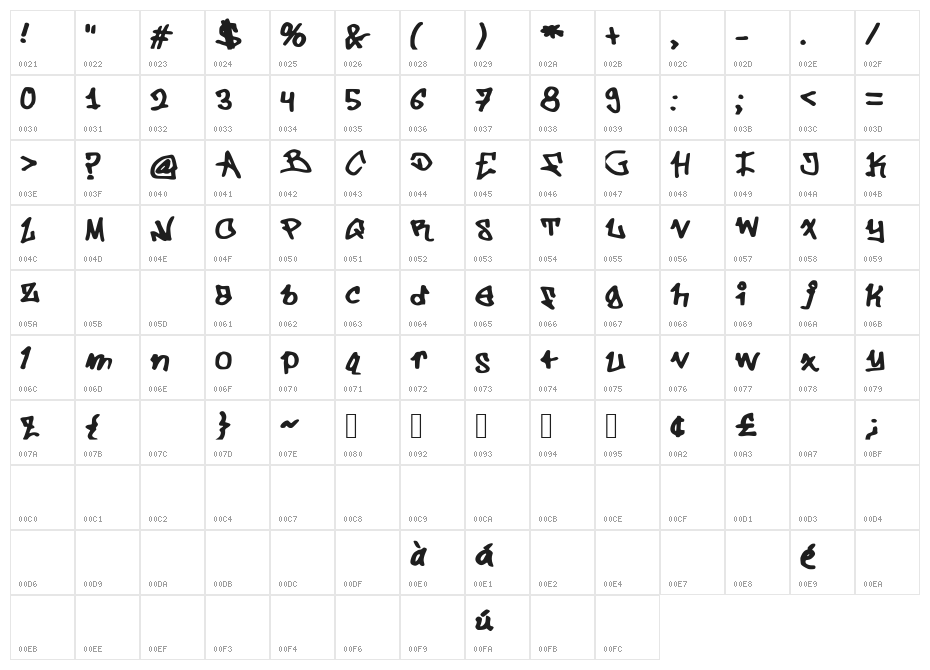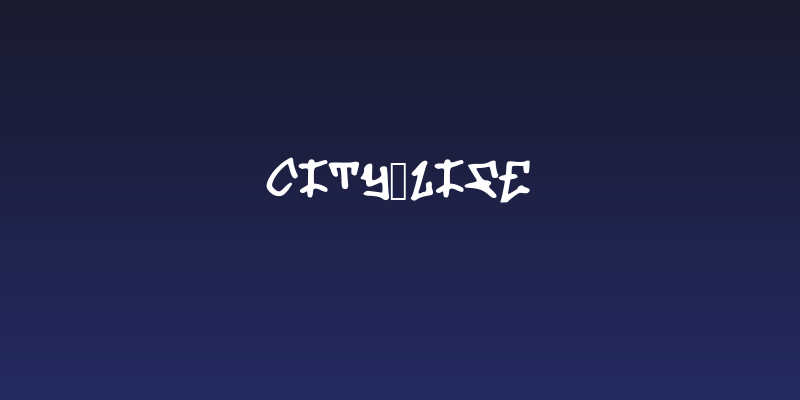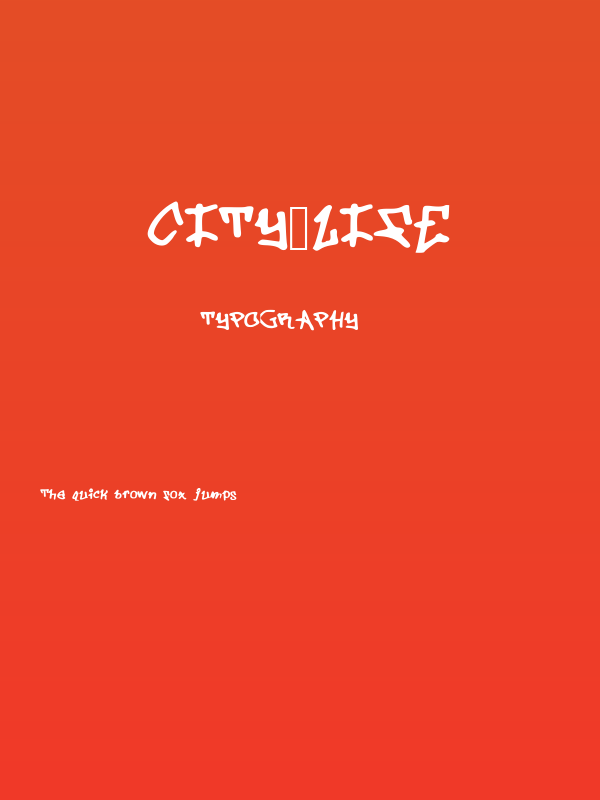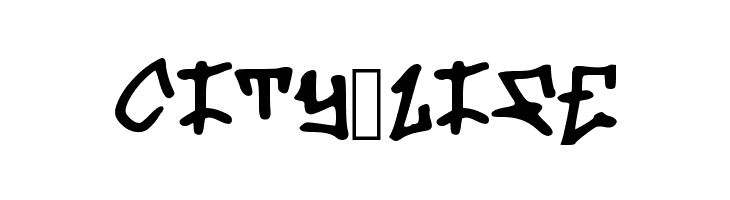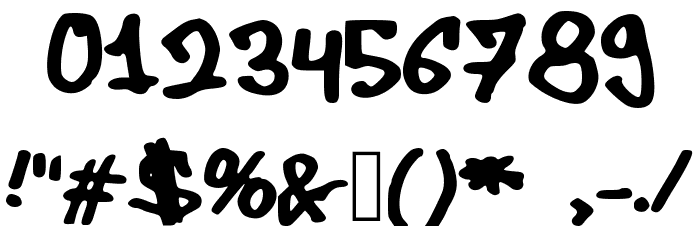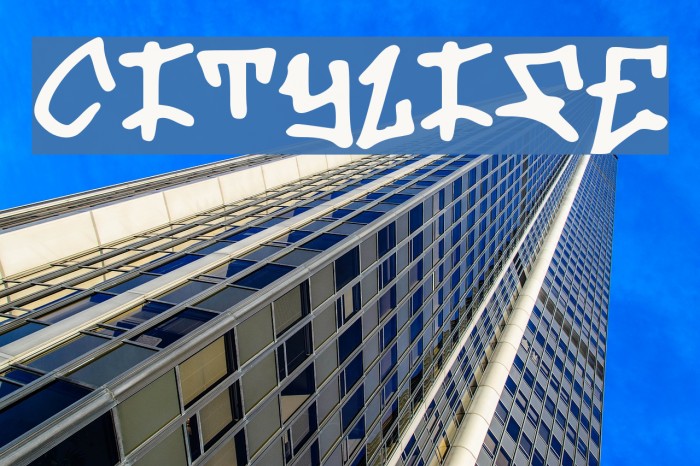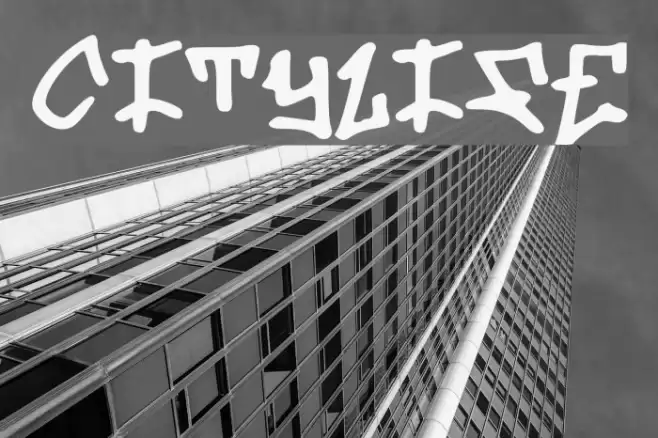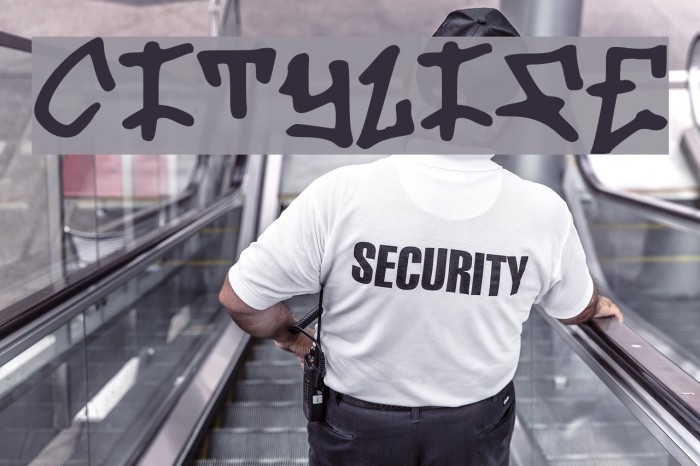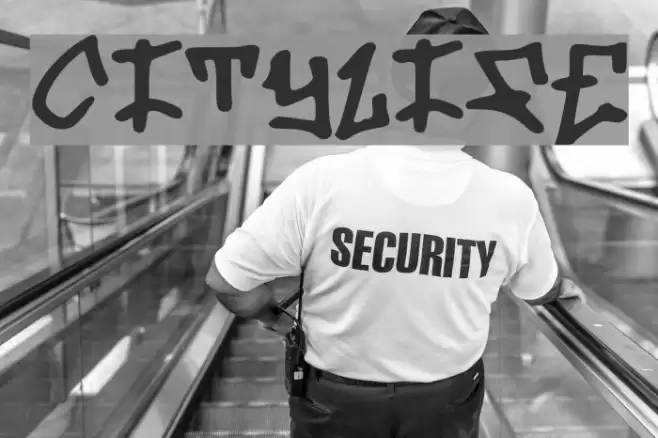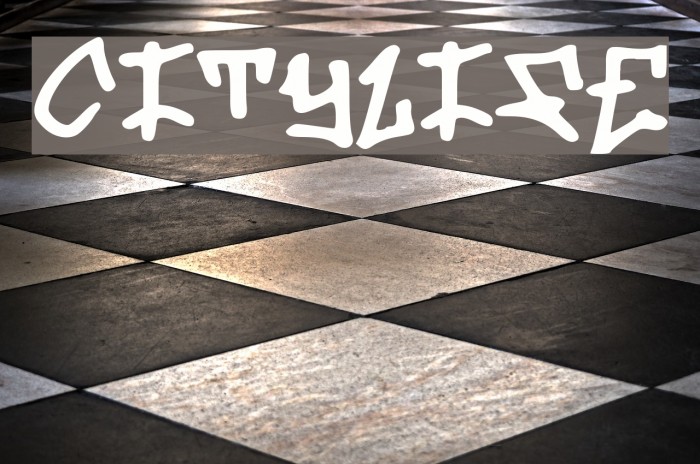
CITY_LIFE Font
| Gesamtstil | Urban, Graffiti, Artistic |
| Vorgeschlagene Projekte | Ideal for street art designs, urban-themed posters, music album covers, and edgy branding projects. |